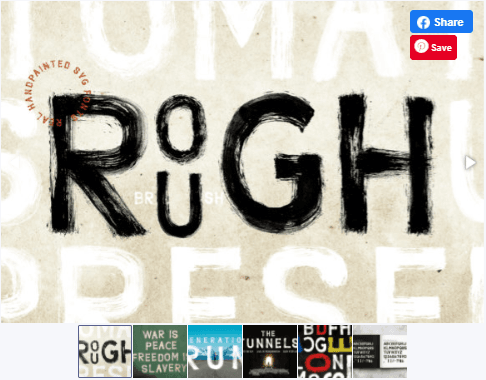
Rough Font
Rough - это смелый и невероятно уникальный дисплейный шрифт. Он отличается простыми и объемными персонажами и, как следствие, подойдет к широкому спектру дизайнов. Единственным ограничением является ваше воображение!